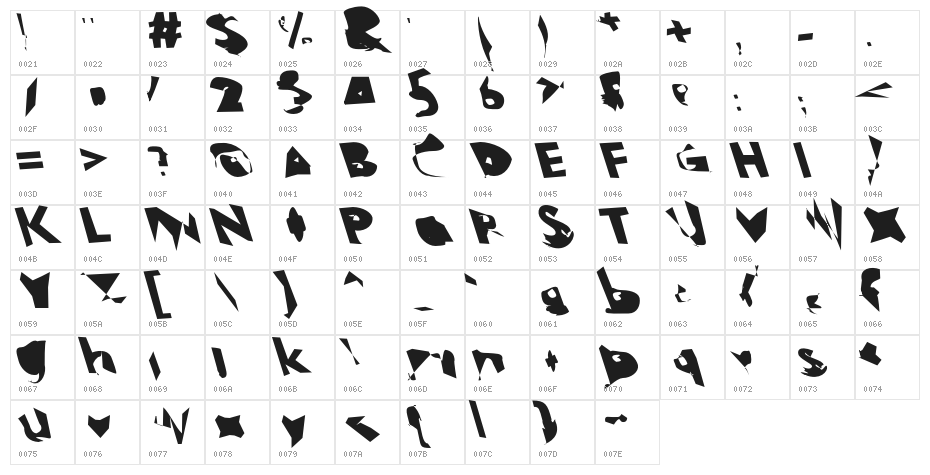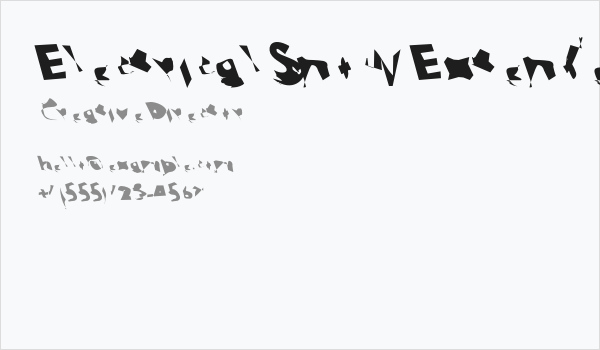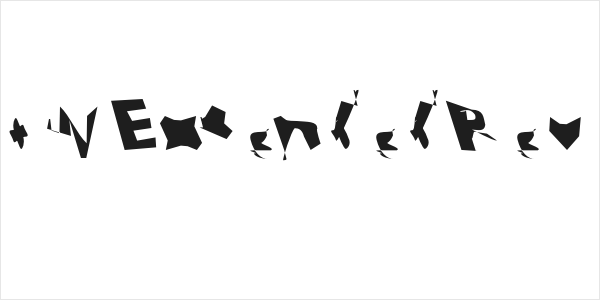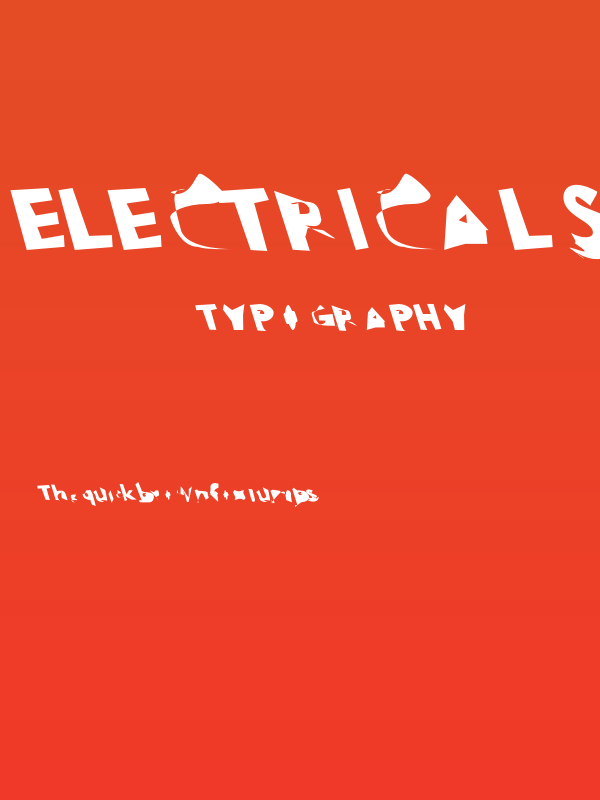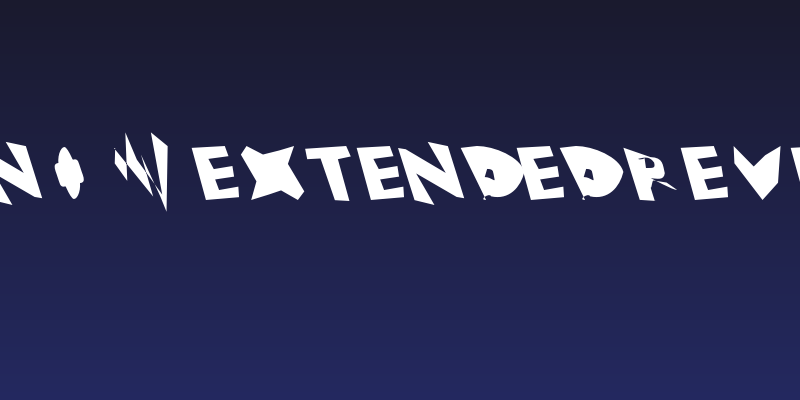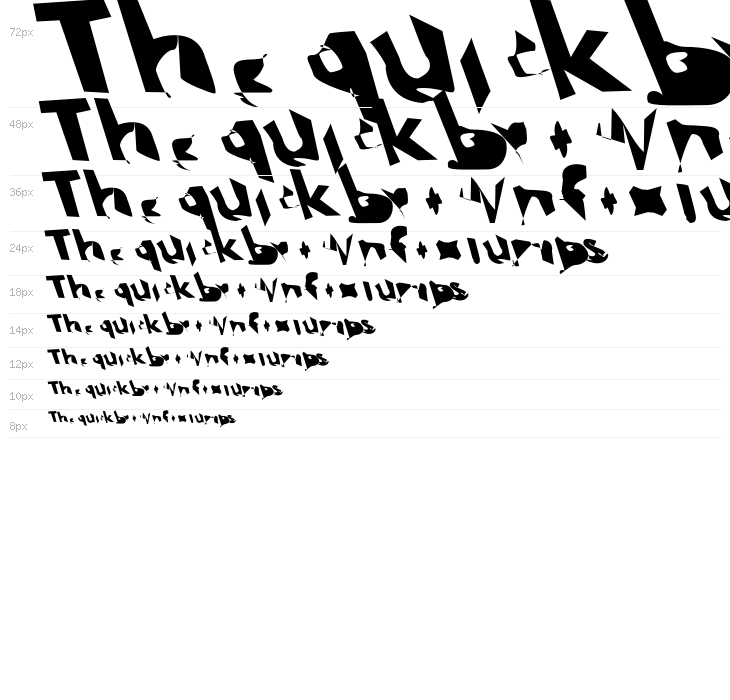
Electrical Snow Extended ReverseOblique Font
✎ Distorted Eroded
| 分类 | Distorted Eroded |
| 宽度 | Expanded |
| 整体风格 | Modern, Edgy |
| 推荐项目 | Ideal for album covers, poster designs, video game graphics, and any project requiring a bold, edgy aesthetic. |